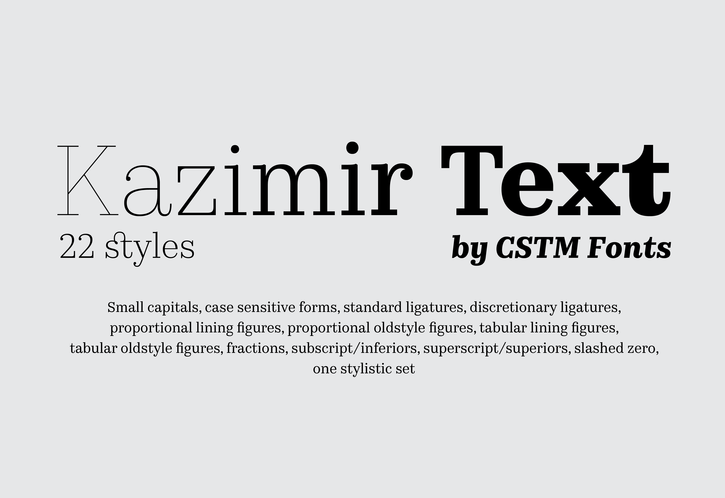
A Kazimir Text™ é uma nova adição à nossa família de fontes serifadas, especialmente projetada para complementar seu amplo acervo de tipos de texto. Esta elegante linhagem moderna foi criada para trazer a perfeição no design editorial e digital. Semelhante ao famoso displayKazimir typeface, Kazimir Text™ é uma fonte de texto que oferece proporções um pouco maiores, contrastes ligeiramente menores e suporte linguístico mais extenso. Ideal para quem busca um tipo sofisticado com elementos minimalistas, a Kazimir Text™ se destaca por sua capacidade de adaptar-se às múltiplas necessidades de design. Com uma gama de 80 caracteres no código fonte, ela oferece suporte a uma variedade incrível de idiomas e tem um grau de compatibilidade extremamente elevado com diversos sistemas operacionais. Adicione ao seu projeto a elegância inegável da Kazimir Text™, garantindo que sua marca ou design fique ainda mais poderoso. Seja em materiais impressos ou digitais, esta fonte é uma escolha versátil para qualquer ambiente de comunicação visual. Com certeza, ela será o complemento perfeito para seu acervo de tipos.